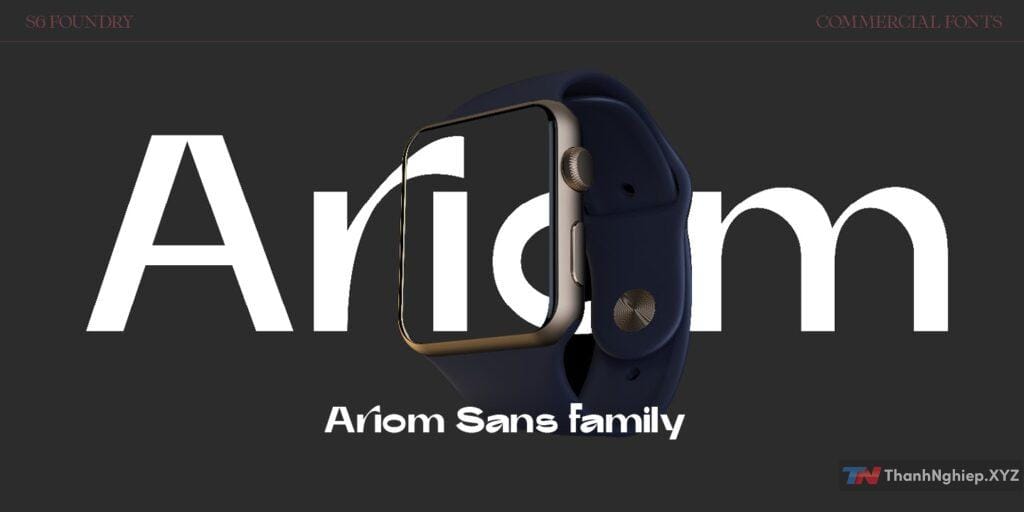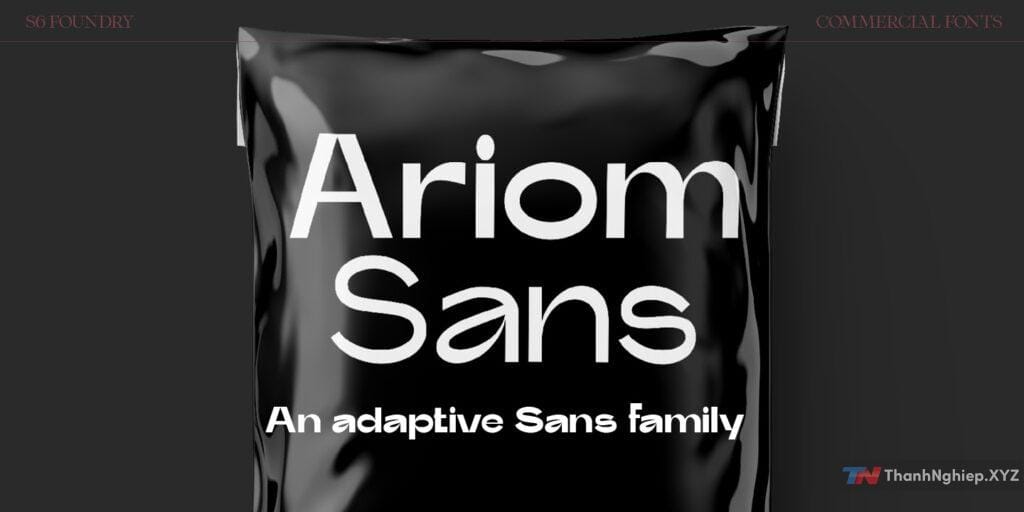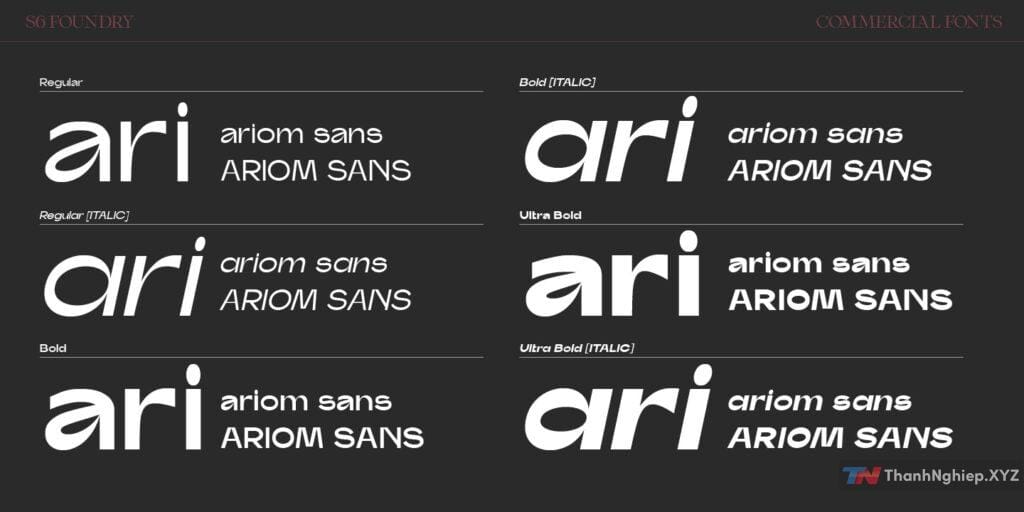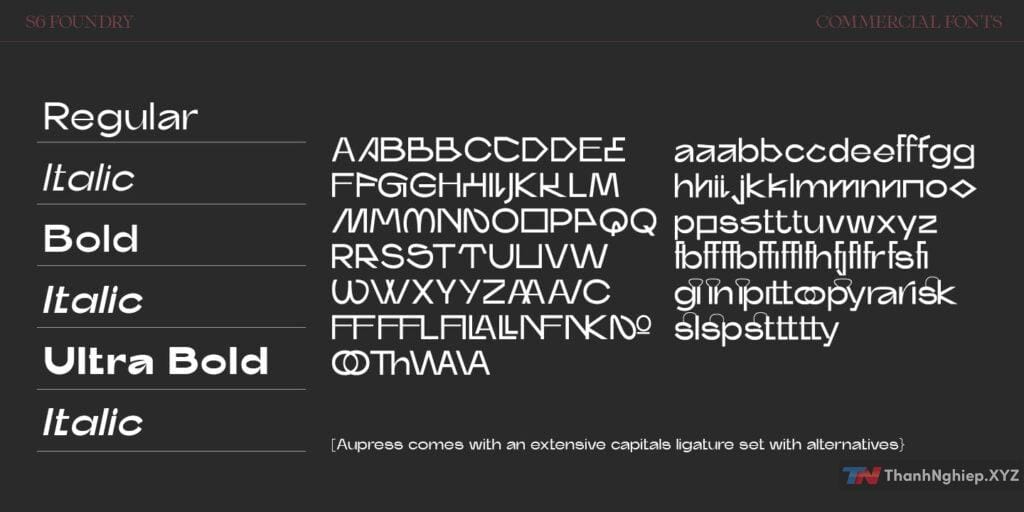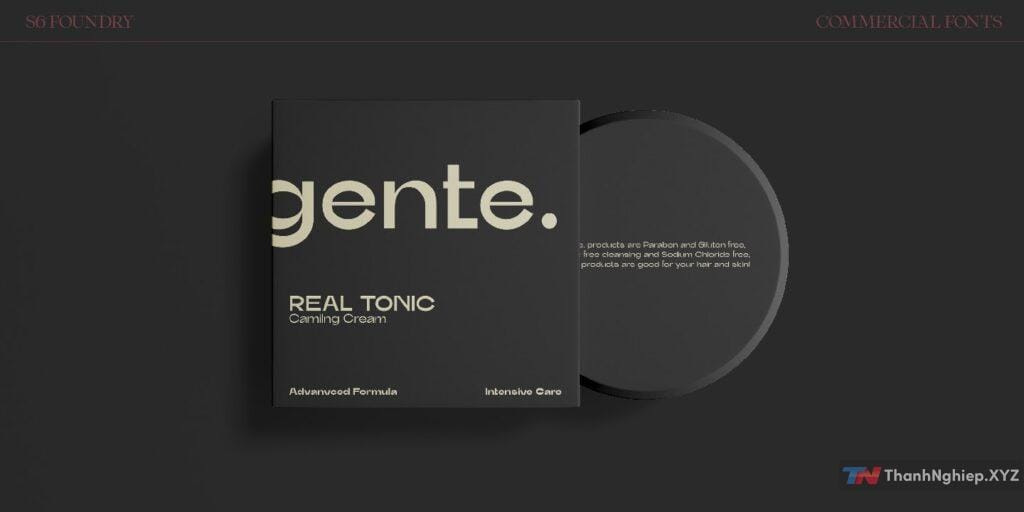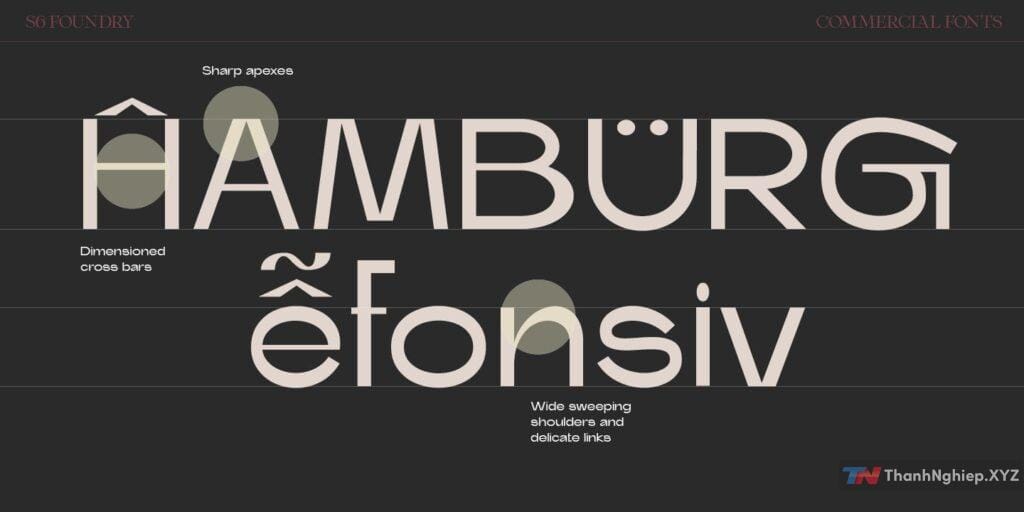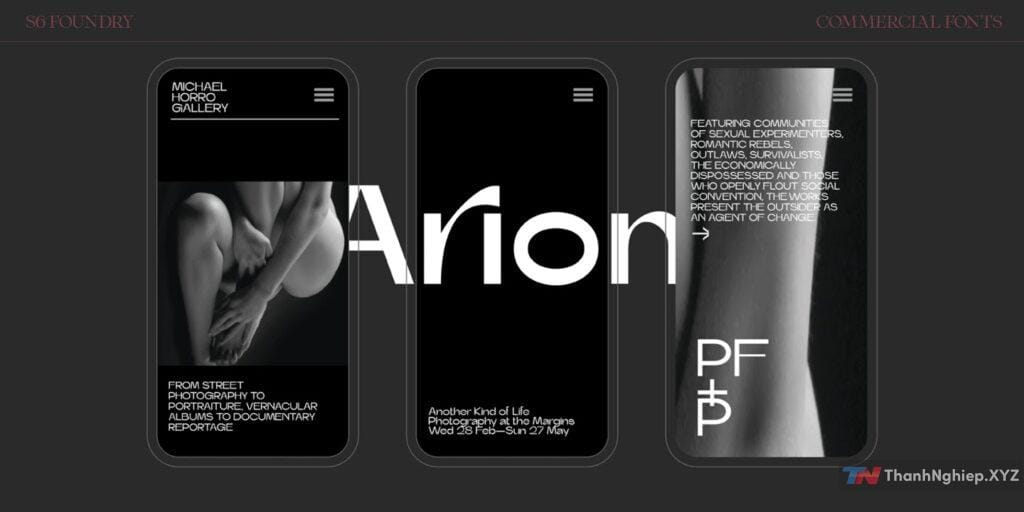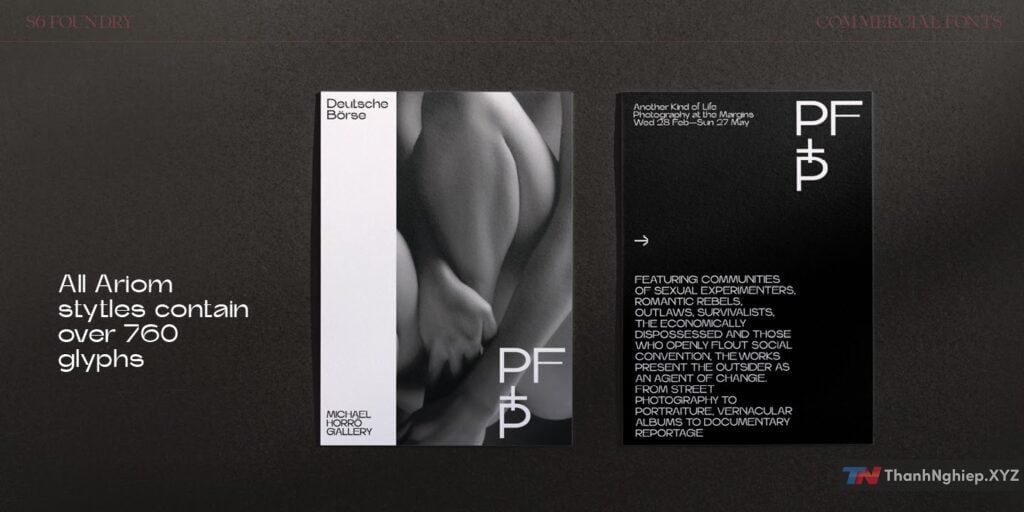
Bạn đã từng rơi vào tình huống đang làm một thiết kế siêu đẹp nhưng bộ font lại không hỗ trợ tiếng Việt, khiến “ê a” thành “ea”, “hớt hải” thành “hôt hai”? Thật là thảm họa, đúng không nào? Đừng lo lắng, vì Ariom Sans Full chính là vị cứu tinh bạn đang tìm kiếm!
Ariom Sans Full có gì đặc biệt?
Hỗ trợ đầy đủ tiếng Việt:
Với bộ ký tự mở rộng, Ariom Sans Full không chỉ giúp bạn viết tiếng Việt mượt mà mà còn giữ nguyên phong cách hiện đại, tinh tế. Từ dấu sắc, dấu huyền, cho đến “ê”, “ơ”, “đ”, tất cả đều được chăm chút cẩn thận.
Thiết kế hiện đại, đa dụng:
Font này có phong cách tối giản (minimalism) nhưng không kém phần ấn tượng. Nó phù hợp với nhiều loại thiết kế như logo, poster, giao diện ứng dụng, bảng hiệu hay thậm chí chỉ là một bài thuyết trình “sang chảnh”.
Đa dạng trọng lượng (weights):
Ariom Sans Full có nhiều trọng lượng khác nhau từ mỏng (Thin) cho đến đậm đà (Bold), giúp bạn dễ dàng phối hợp trong cùng một thiết kế mà không sợ nhàm chán.
Tối ưu cho thiết kế digital và in ấn:
Font này hiển thị rõ nét cả trên màn hình lẫn trên giấy in. Dù là thiết kế website hay một tấm banner quảng cáo khổ lớn, Ariom Sans Full đều làm tốt nhiệm vụ của mình.
Phong cách cá tính nhưng dễ đọc:
Sự kết hợp giữa các đường cong mềm mại và các nét thẳng góc cạnh mang lại cảm giác vừa chuyên nghiệp, vừa thân thiện. Dùng font này là bạn đang nói: “Tôi hiện đại, nhưng không khó gần.”
Tại sao bạn nên chọn Ariom Sans Full?
Hãy thử tưởng tượng: Bạn cần một font vừa đẹp mắt, vừa hỗ trợ tiếng Việt để tránh việc phải “chữa cháy” từng chữ một. Ariom Sans Full chính là câu trả lời! Đây là “người bạn đồng hành” lý tưởng để bạn không còn phải đau đầu mỗi khi thiết kế cho thị trường Việt Nam.
Không chỉ vậy, việc sở hữu bộ font này còn giúp bạn tiết kiệm thời gian tìm kiếm và thử nghiệm, để tập trung sáng tạo nội dung hơn. Ai mà chẳng thích một bộ font vừa đẹp, vừa “chất”, đúng không?
Ariom Sans Full chính là lựa chọn sáng suốt!
Nếu bạn là một nhà thiết kế đang tìm kiếm sự khác biệt hoặc chỉ đơn giản là muốn mọi thứ trở nên đúng chuẩn, thì còn chần chừ gì nữa? Hãy để Ariom Sans Full trở thành “trợ lý đắc lực” của bạn trên hành trình sáng tạo. Còn nếu bạn không phải nhà thiết kế? Không sao, dùng font này để soạn thảo bài viết hay thiệp mời cũng chất chơi người dơi lắm!
Cầm trong tay Ariom Sans Full là bạn đã nắm trong tay một phần sức mạnh sáng tạo vô biên. Vì vậy, hãy tải ngay và trải nghiệm để thấy sự “lợi hại” của bộ font này!
Chú ý: Hỗ trợ 100% tiếng Việt, nhưng việc bạn có sáng tạo được 100% hay không thì… tùy bạn nhé! 😉